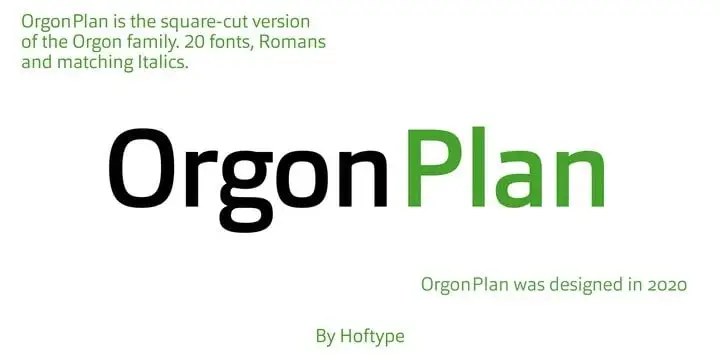
Orgon Plan Sans Serif Font
A Orgon Plan Sans Serif é uma tipografia sans-serif criada a partir do Orgon, que já ganhou popularidade entre os designers. O Orgon tem sido aclamado pela sua simplicidade e facilidade de leitura, tornando-o um ícone em diversas aplicações visuais. Agora, vem o Orgon Plan como seu irmão mais novo: a Orgon Plan é uma versão squarish do Orgon, representando a essência da tipografia em forma retangular. Como um complemento ao sucesso da família Orgon, a Orgon Plan foi lançada no ano de 2020 e traz uma nova perspectiva para designers buscando personalidades distintas. Seja para rótulos de produtos ou gráficos publicitários, esta tipografia suave mas firme é perfeita para quem busca uma fonte versátil que combine modernidade com elegância, sem perder a facilidade de leitura característica da família Orgon.